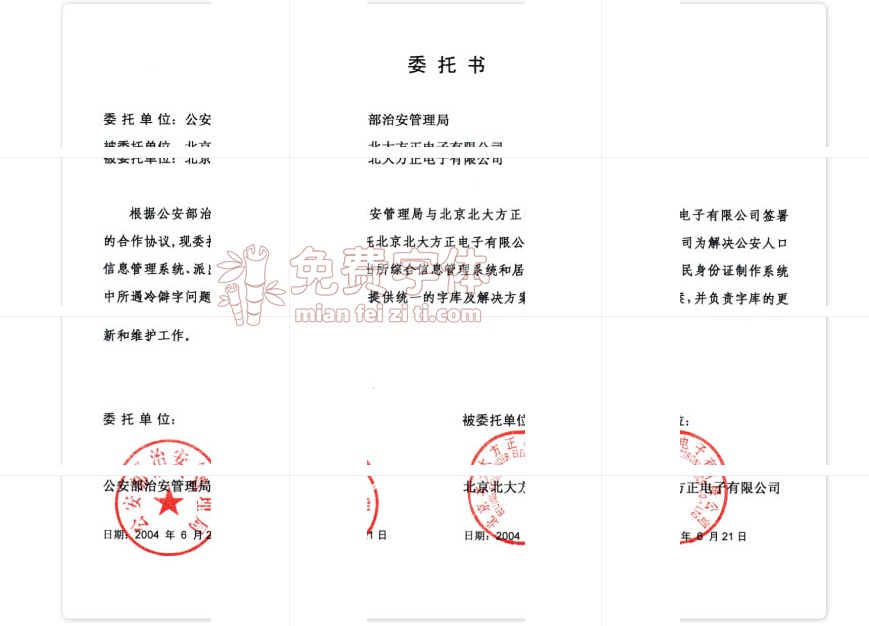
方正宋体-人口信息字体介绍鉴赏字体鉴赏
为了解决生僻字姓名,方正字体公司开发的方正宋体-人口信息。
人口信息冷僻字解决方案
[概述]
2003年国家信息化领导小组第一次会议决定,把电子政务建设作为今后一个时期我国信息化工作的重点,政府先行,带动国民经济和社会发展信息化。同时发布了《关于我国电子政务建设的指导意见》明确提出国家要组织编制政务信息资源建设专项,设计电子政务信息资源目录体系与交换体系;启动人口基础信息库、法人单位基础信息库、自然资源和空间地理基础信息库、宏观经济数据库的建设。
人口基本信息库由公安部联合计划生育委员会、国家税务总局、劳动和社会保障部以及国家民政部等部委共同建造。该信息库的核心内容将包括我国13亿常住公民的姓名、性别、身份证号码、出生年月、出生地和民族等六项基本信息。更多的信息将在相关部委的协作下在基本信息的基础上作进一步的扩展。
人口基本信息库也为正在普及的具有机读和计算机网络核查功能的第二代居民身份证建立了数据平台。由于使用的计算机系统多数采用GBK编码的字库,共收录汉字21003个,不能完全适应处理人名、地名的需要。以前,各地公安机关在制作居民身份证时,把遇到的姓名和住址的生僻字通过人口信息管理系统按照一定的编码规则进行造字,解决制证过程中的个人信息打印问题。由于第二代身份证采用了非接触式集成电路,需要对全国人名、地名中的生僻字进行整理、规范,建立统一生僻字库或扩充原有字库,才能实现全国范围内生僻字的存储、读取,因此需要对现有字库进行扩充并提供有效的补字系统。
解决人口信息生僻字问题,需要对全国人名、地名中的生僻字进行收集整理、查重审定、建立统一生僻字库或扩充原有字库、编程实现。收集整理即收集整理全国人口信息中的生僻字。查重审定即各地使用的系统采用字库不同,缺字的状况也不同,上报的生僻字中,一部分汉字重复或在新的字库中已经收录,需要把这部分字删除。扩充字库、编程实现即将字库中尚不存在的生僻字加入字库,由于生僻字在目前计算机系统中没有收录,需要选择编码方案对这些字进行编码管理。
另外,实际工作中会遇到新的生僻字,需要有高效实用的补字系统,能够尽快补字,并能保证字体的统一性。将生僻字加入了字库以后,还需要一种简便易用的输入法,让操作人员可以方便的输入这些汉字。
正是在这样的情况下,北大方正公司受公安部的委托,发挥自身在中文字库开发方面的技术优势,将公安部从全国各地派出所收集上来的人名和地名生僻字进行整理、分析,根据人口信息系统建设的实际情况、二代身份证制证的要求和系统运行环境,制定了方正人口信息字库解决方案。该方案具有通用、易用和标准的特点,不仅在适合公安系统得到广泛使用,也必将为其它行业解决生僻字问题带来极大的帮助。
[人口信息用字方案及工作流程]
一、人口信息用字解决方案主要包括四个部分:
1.  人口信息用字库
2.  人口信息用字的输入法
3.  自动安装和升级程序
4.  补字服务
下面分别介绍:
1.  人口信息用字库
字库由编码方式和字符集两部分来决定。
在人口信息专用汉字字库“方正宋体-人口信息”的现有版本中,共收录汉字32309个,包括GBK编码标准汉字21003个,CJK统一汉字扩充A 6582个,GB13000用户自定义区4724字,其中GBK用户自定义区1481字,涵盖了各地整理上报的全部地名用字、姓氏用字和使用频度较高的人名用字。
2.  配合人口信息用字的输入法
人口信息用字符集需要有专门的输入方法才能正确输入。我们专门开发了新典码输入法解决这个问题。方正新典码输入法根据汉字的部首、笔画、笔顺、笔画数等特征作输入汉字的检索条件,采用交互式图形界面,通过不断选择目标汉字的特征组合,最终通过鼠标点击实现汉字输入。这种输入法以鼠标为输入工具,界面直观,对输入人口信息用字不需要记忆任何字根或编码,便于普通用户的学习和掌握。
新典码输入法是为了解决人口信息用字输入问题而专门开发的,该输入法是其它输入方法的补充。用户在日常使用时还是使用原来用惯的输入法,只有在需要输入人口信息用字时才调用这一输入法。所以不会影响工作效率。
3.  自动安装和升级程序
4.  补字服务
对于意外发生的补字需求,北大方正提供相应的补字服务工作。
由使用单位向北大方正提出补字要求,同时提供原始字形。北大方正向使用单位提供字库的时间由双方协商决定。
可采取实时提供方式(北大方正于收到补字要求后5个工作日内提供)。也可采取定期提供方式(周期为每月或每季度)。北大方正提供补字的同时提供输入法。
二、工作流程:
人口信息用字方案的实际工作流程如下图: